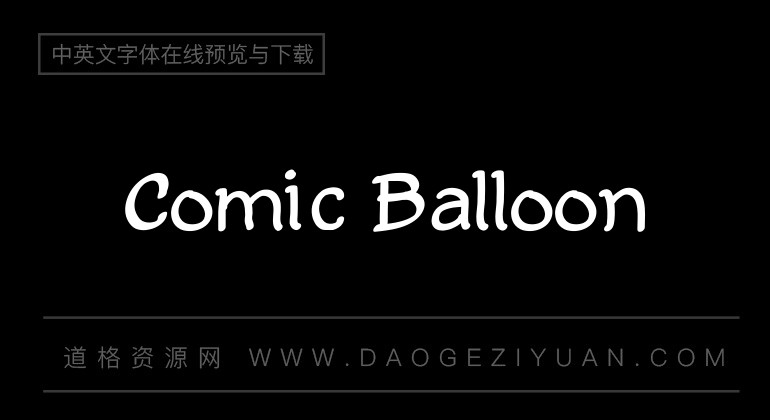
Comic Balloon 字体是一种漫画风格的字体,它被设计用于漫画、卡通、游戏等视觉媒体中。它具有活泼、灵活的外观,可以帮助创造出更加有趣、更加生动的视觉效果。它的字体特点主要集中在文字的粗细、轮廓和空隙上,其中空隙可以更加凸显文字的轮廓,使文字更加易于阅读。Comic Balloon 字体也可以结合漫画的元素,如气泡、箭头等,来增加更多的视觉效果。内容介绍
Comic Balloon是一款非常不错的手写艺术字体,具有很好的视觉感,适合于文化类的宣传设计、商业类品牌的广告和产品包装设计以及个性化文字排版等较多场景。